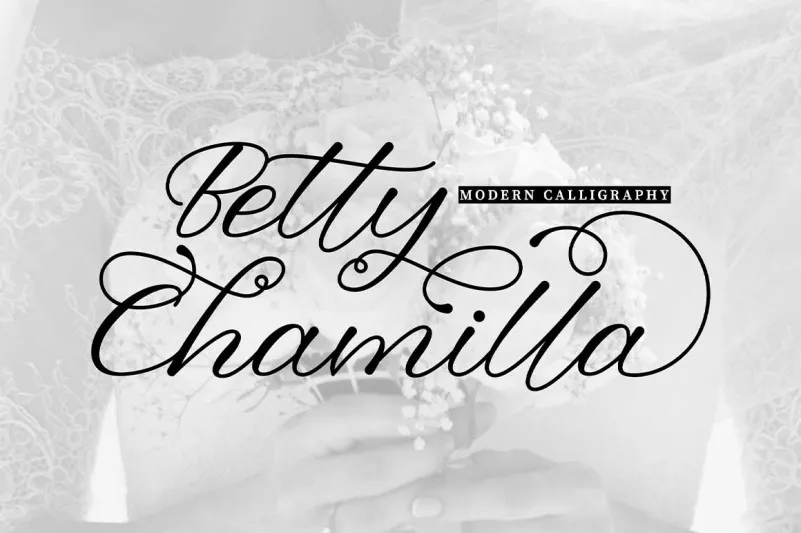
Betty Chamilla Font – Download Grátis
A Betty Chamilla Font é uma elegante tipografia script criada pela JunCreative, apresentando um aspecto romântico e moderno com swashes na abertura e encerramento que dão ao texto um ar sofisticado e único. Esta fonte traz uma aparência natural que se adapta perfeitamente a diversos projetos, seja para gráficos de marketing, arte digital ou até mesmo design editorial. Com sua simplicidade e elegância, esta fonte é ideal tanto para criações profissionais quanto para uma expressão pessoal mais descontraída. Descubra o fascínio da Betty Chamilla Font para personalizar seu trabalho com um toque único e romântico.